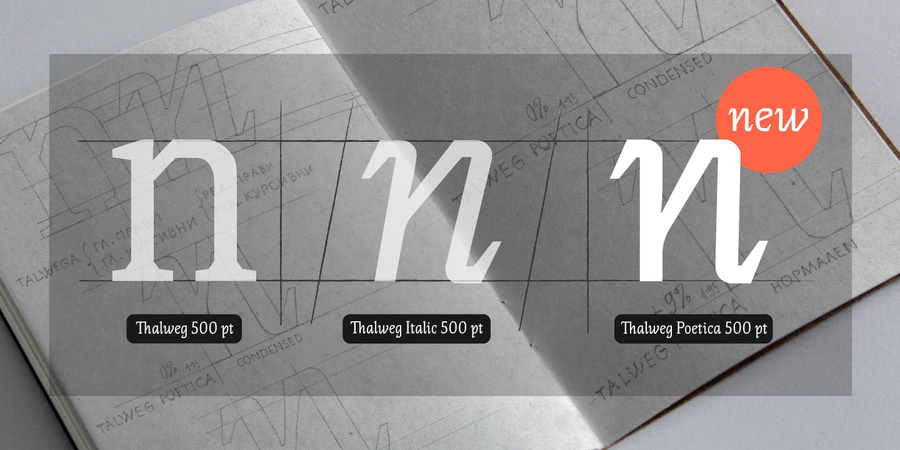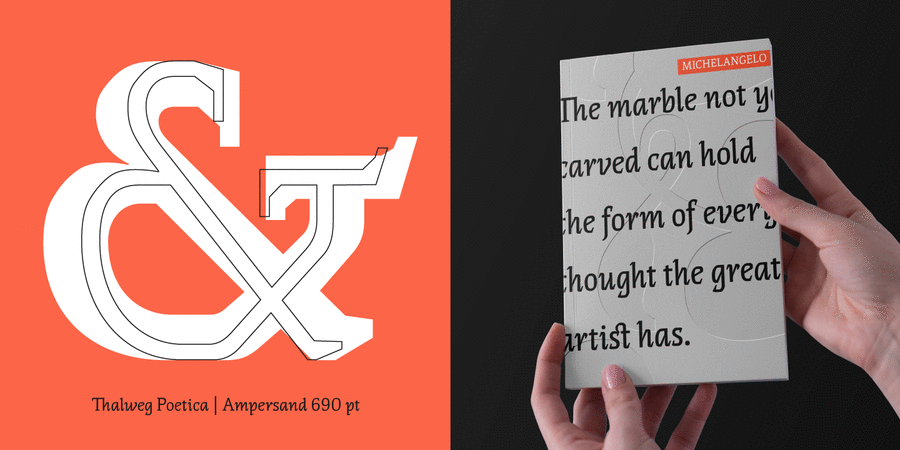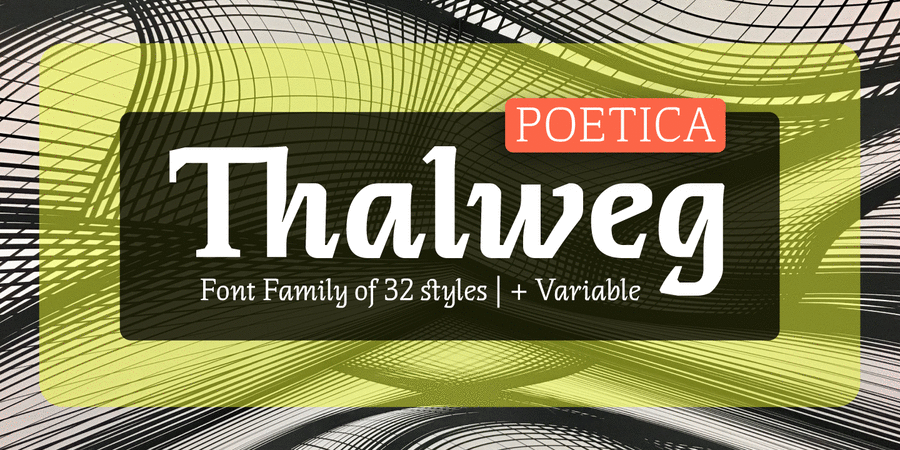
Thalweg Poetica (33 шрифта)
Thalweg Poetica – це шрифтова реконструкція, заснована на історії, створеній в 1993 році болгарським художником Іваном Кьосєвим. Це продовження гарнітури Thalweg, створеної у 2020 році. Форма символів поєднує конструкцію прямих накреслень Thalweg та її курсивних накреслень. Новий шрифт ідеально поєднується з сімейством Talweg і дає дизайнерам нові можливості.
Thalweg Poetica містить 4 варіанти ширини (звичайний, напівстиснений, стиснений та надстиснений) та 8 насиченостей від тонкого до чорного. Кожне накреслення містить більше 1100 гліфів. Шрифт поставляється з розширеним охопленням латинки, кирилиці та грецької абетки. Всі накреслення спеціально призначені для складної професійної типографії з використанням функцій опентайп, включаючи: капитель, лігатури, дискретні лігатури, верхні індекси, нижні індекси, табличні цифри, мінускульні цифри, цифри в колах, стрілки, символи валют і дроби. Сімейство Thalweg Poetica ідеально підходить для заголовків, дрібного тексту, книг і журналів, брендингу, плакатів, веб-дизайну. Накреслення Regular і Medium ідеально підходять для основного тексту й надають йому цікавої текстури. Шрифт розробила Ані Дімітрова в 2022 році.
Асоціації з сімейством шрифтів Thalweg PoeticaОсобистість і характер гарнітури:
освічений, серйозний, розумний, міський, ритмічний, динамічний, різкий, чіткий, характерний, оригінальний, самобутній, осінній, гострий, колючий, незвичайний, дивний, макабричний, декоративний, кріповий, колоритний, творчий, чаклунський, магічний, химерний, ремісничий, складний, загадковий, експериментальний, історичний, ролевий, середньовічний, старовинний, казковий, артистичний, цікавий, чарівний, художній, виразний, тонкий, легкий, стійкий, худий, сухий, дротяний, ламаний, сильний, міцний, важливий, авторитетний, значний, суворий, жорсткий, важкий, щільний, помітний, яскравий, активний